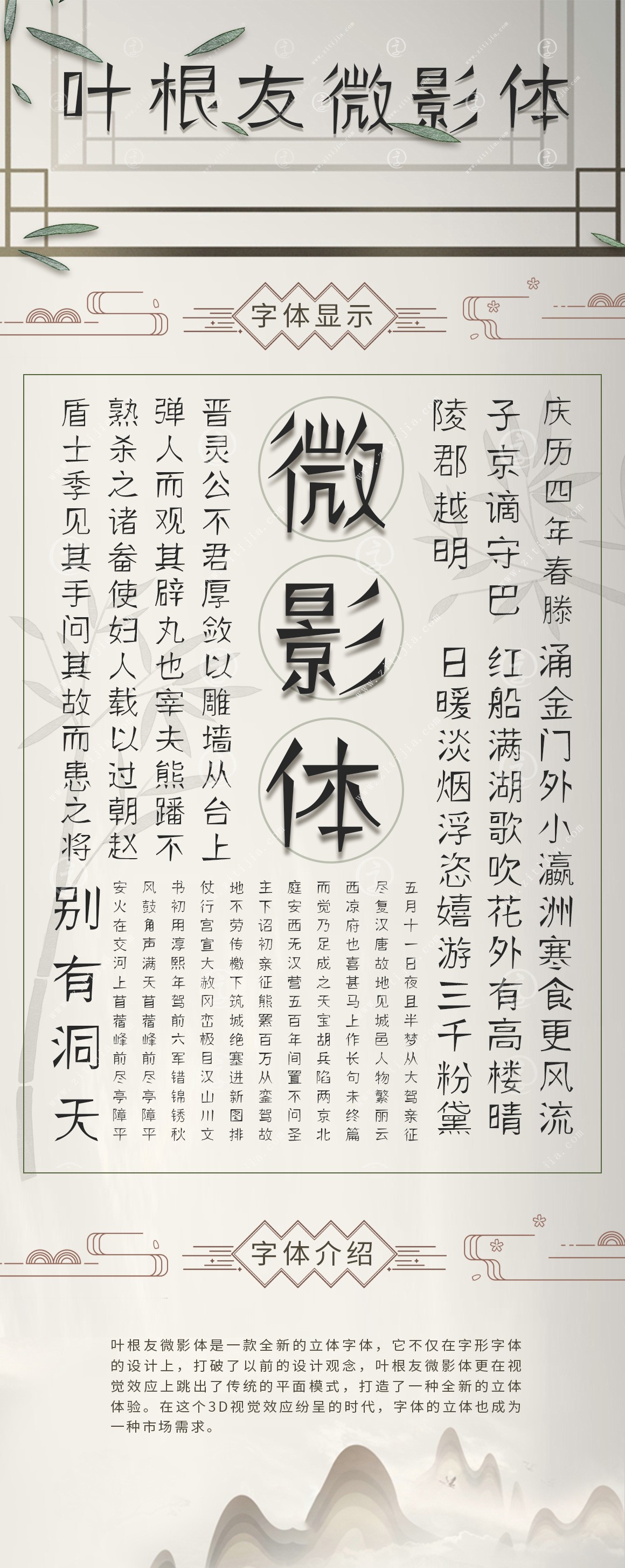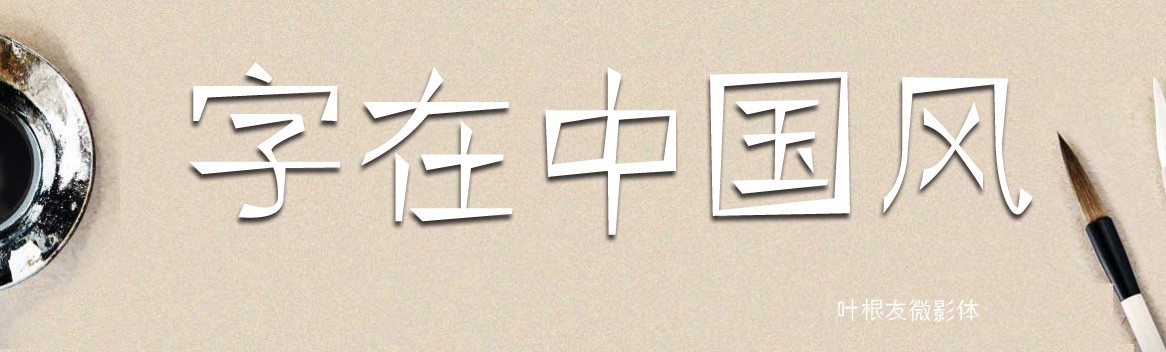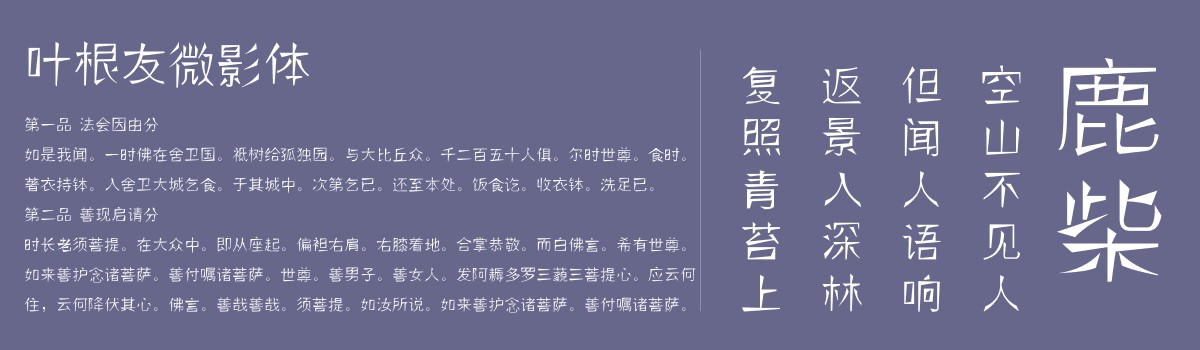
叶根友微影
创作年代:2013年
字体字数:6763个中文汉字以及其他英文字母和阿拉伯数字
字体介绍
叶根友微影体是一款全新的立体字体,它不仅在字形字体的设计上,打破了以前的设计观念,叶根友微影体更在视觉效应上跳出了传统的平面模式,打造了一种全新的立体体验。在这个3D视觉效应纷呈的时代,字体的立体也成为一种市场需求。
字体应用